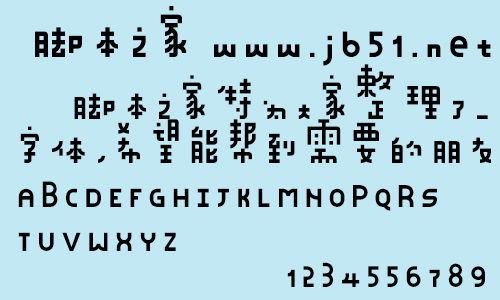
方正仙陣體簡字體是由方正字體開發(fā)的基于像素的藝術(shù)字體,這款字體整體造型看上去非常的奇特,撇捺點(diǎn)進(jìn)行了1/4圓的圓弧設(shè)計(jì),折鉤部分設(shè)計(jì)成圓角,適合應(yīng)用于藝術(shù)設(shè)計(jì)、平面宣傳設(shè)計(jì)、網(wǎng)頁設(shè)計(jì)、兒童書籍等領(lǐng)域,需要的朋友可以前來本站下載。